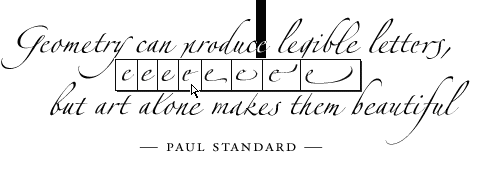
Bonjour Thierry Bouche <thierry.bouche@xxxxxxxxxxxxxxx>, Le 2002-09-02 17:40:01, vous avez écrit : > TL> Sans mauvaise foi : avec TeX, il est vraiment simple d'insérer des > TL> caractères alternatifs (lettres ornées, initiales, finales, &c.) ? > > oui. > > TL> Comment fait-on quand on ne les voit pas ? > > sais pas. Daignerez-vous nous dire quels mots de plus ? Je joins un exemple avec Zapfino, qui sortira en OpenType l'an prochain (tiré de http://www.microsoft.com/typography/developers/opentype/over.htm) : j'admets volontiers que les « fontes virtuelles » ont bien du mérite, mais l'interface de TeX peut-elle vraiment offrir ça ? -- Cordialement, Thomas Linard